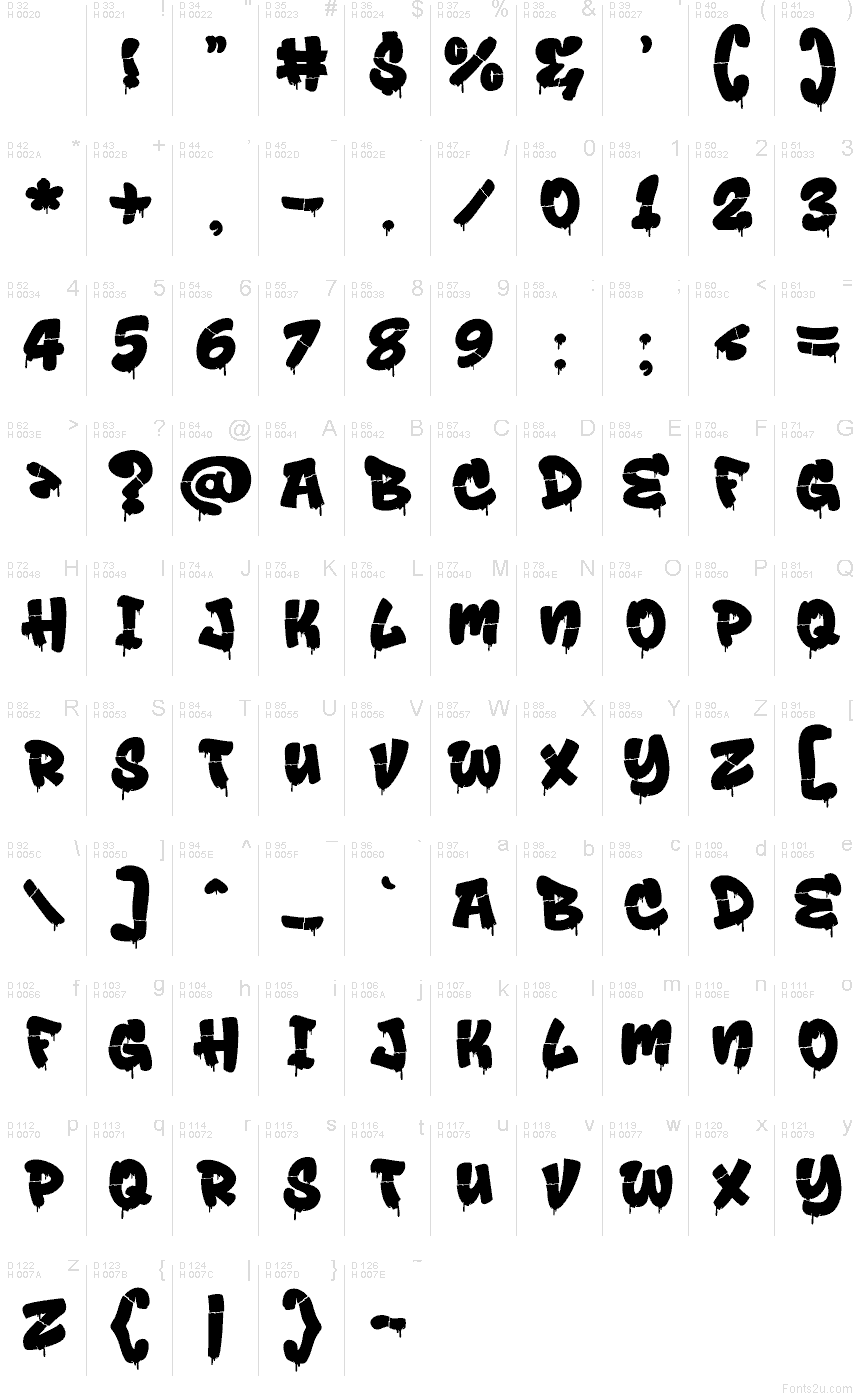
Il font Drop Shade Melt di Muhammad Panji Ramdhani di Sipanji x Cikareotype trasuda un'energia urbana cruda, come vernice fresca che cola da un muro. Le lettere sono audaci e arrotondate, con tagli viscosi e gocce pendenti che aggiungono movimento anche in una singola parola. È un font graffiti gratuito, e la sua silhouette umida e inchiostrata fa sì che i tuoi titoli colpiscano forte e subito.
Usando Drop Shade Melt, darai una marcia in più a poster, grafiche skate o streetwear, copertine di album, miniature YouTube, set di adesivi, volantini per eventi e promozioni social incisive. Questo font gratuito si legge al meglio mantenendo la spaziatura leggermente aperta per dare modo al font di "colare". Abbinalo a un sans serif pulito e stretto per le didascalie, così che il caos resti circoscritto ai titoli.